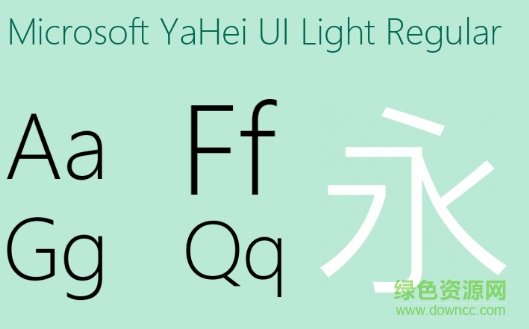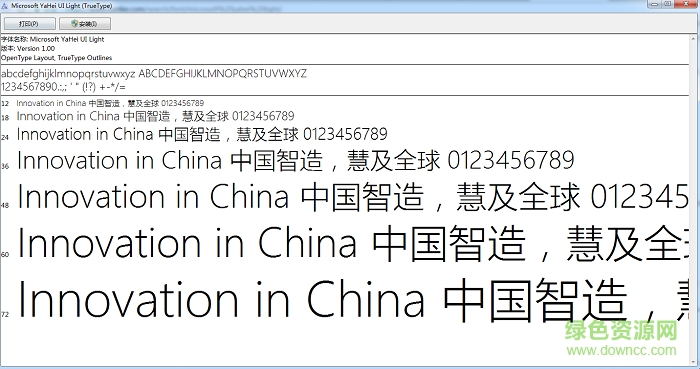
microsoftyaheilight字體是一款現(xiàn)代感十足的微軟雅黑亮體字體,這款字體分辨率高,邊線平滑干凈,屏幕顯示效果清晰明亮,需要的朋友快來下載吧!
微軟雅黑支持GBK字符集,包含了Unicode的所有 20902個(gè)中文字符以及中國國家標(biāo)準(zhǔn)化組織添加的大約 80個(gè)中文字符,還包含了Big5的繁體中文字符和GB2312中的簡體中文字符。